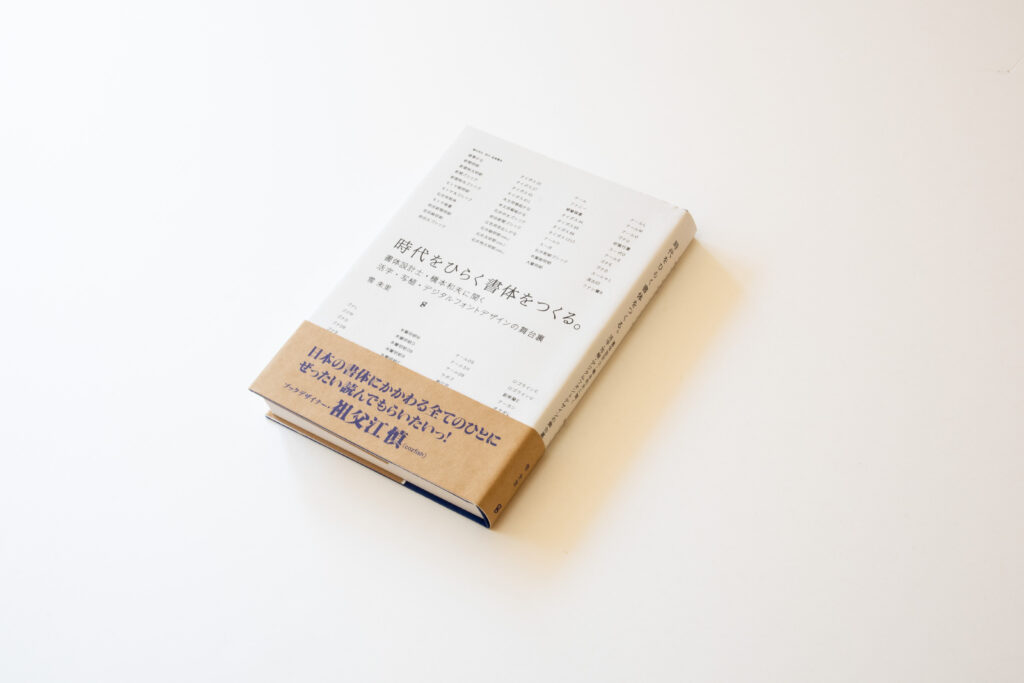
TPの書庫から『時代をひらく書体をつくる。』
今回は、雪朱里著の『時代をひらく書体をつくる。 書体設計士・橋本和夫に聞く 活字・写植・デジタルフォントデザインの舞台裏』を紹介します。
本書は、活字・写植・デジタルフォントの三世代に渡って書体を制作、監修し、重要な部分を築いてきた橋本和夫さんのインタビューを通して日本語書体の流れについて触れられる内容になっています。
橋本さんが携わり、各時代を取り巻く環境のもとで作られ使われた数々の書体がどのように生まれたかや、現在と地続きの書体制作の現場の細かい内容も載っており、自分の日々の仕事を振り返りながら読みました。
書道やレタリングの文字との違いや書体としての文字に求められること、品質の高い書体を作ることについて書かれているところを読み、文字を作る中でひとまとまりの「書体」としての意識が欠けていたときに理解しているつもりで分かっていなかった部分に気づくことが多かったです。 書体を作る人や書体に関わる人へ橋本さんからの言葉が詰まった一冊でした。
堅いと思われるような書体デザインの流れや歴史でも、ページごとに専門用語の解説や図版なども豊富に載っているので、日本語書体について少し踏み込んで知りたい方やこれから書体を作りたいと考えている方にもおすすめです。
『時代をひらく書体をつくる。』と『ぼくのつくった書体の話』の二書を読めば、写真植字からデジタルフォントに至る和文書体のデザイン史を、おおよそ見渡すことができる。橋本和夫、小塚昌彦、両氏が果たした役割の大きさについては書籍を読んでいただくとして、今後の課題は、ここに含まれない重要な書体とその作り手に関する記録ということになろうかと思う。
ここ十数年は、字游工房の鳥海修さんとフォントワークスの藤田重信さんの露出度が突出しており、同世代の優れた書体デザイナーである金井和夫さん、佐藤豊さん、今田欣一さんの取り組みが語られる場面は目立って少ない。
橋本さんと小塚さんの仕事が金属活字の系譜にあるとすれば、鳥海さん始め次の世代の書体デザイナーには、レタリングと写真植字のありようが少なからず影響を及ぼしていると考えられる。書体を形なさしめる技術および時代背景に思いを致すという意味でも、『時代をひらく書体をつくる。』と『ぼくのつくった書体の話』の価値は高いといえよう。
『書体をひらく書体をつくる。 書体設計士・橋本和夫に聞く 活字・写植・デジタルフォントデザインの舞台裏』